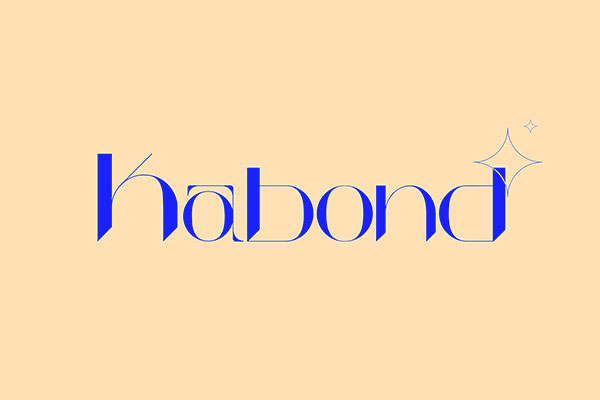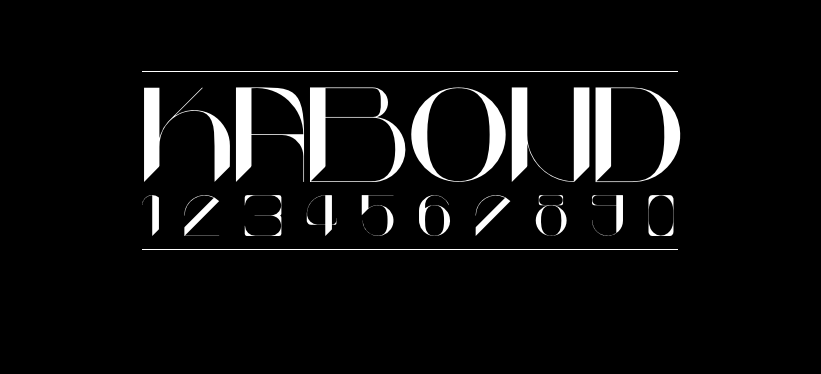
Kabond
Kabond字体介绍
Kabond的作者是法国的Nicolas Silvian,这是一种新的实验字体。Kabond这种独特的sans具有简洁的线条和动态角度,非常适合您的下一个品牌,网页设计或促销项目。Kabond字体首发于Behance,Kabond字体的发布页只写free download,没有写明字体的商用授权方式。为了确认是否可以商用,找到作者的Instgram主页,作者在主页上回复了关于“是否可以免费商用”的咨询,确认为可以免费商用的。所以大家放心下载吧!
Kabond字体应用示例